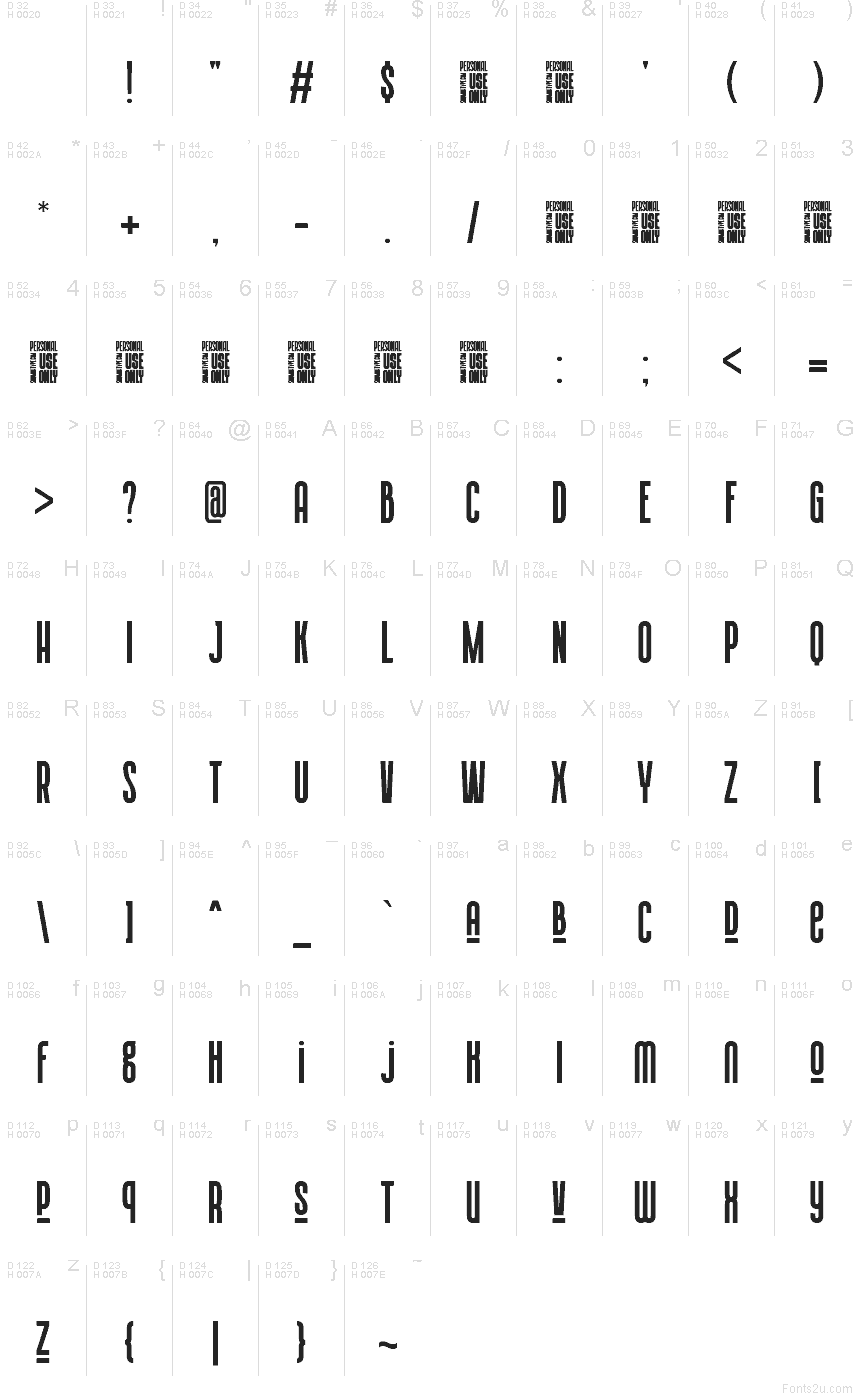
Lonedruida od Salamahtype je bezplatné, úzké nadpisové písmo s vysokými písmeny a hravým retro prohnutím. Jeho úzké tahy přecházejí v zaoblené oblouky a pak klesají do dlouhých svislých linií, které písmu dodávají uvolněnou plakátovou siluetu.
Dokáže proměnit hudební plakát nebo název festivalu v součást uměleckého díla, zejména v kombinaci s křivkami a vzory inspirovanými 70. lety. Protažené tvary se hodí také pro módní branding. Obaly albu a festivalový merchandise získávají díky jeho nepravidelným proporcím podobně nekonvenční, ručně vyrobený šmrnc.